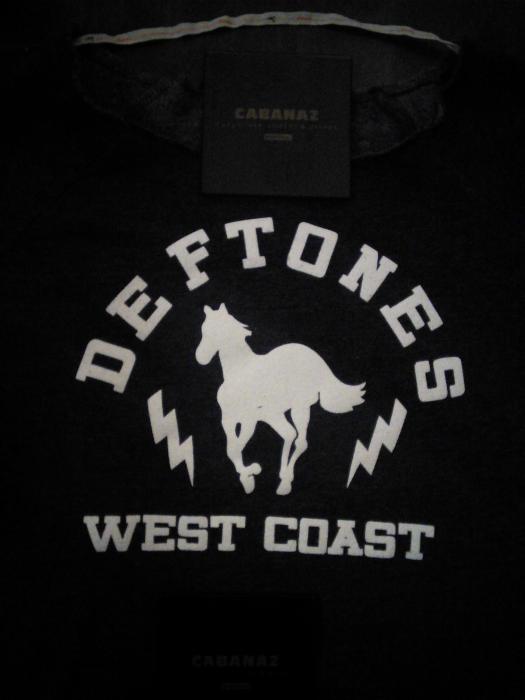
Suche Schrift Deftones, ähnlich Rockwell
Suche die Schrift vom Pulli oder eine ähnliche. Ist ja so Richtung Rockwell, aber das Versal D und S sind eckiger.